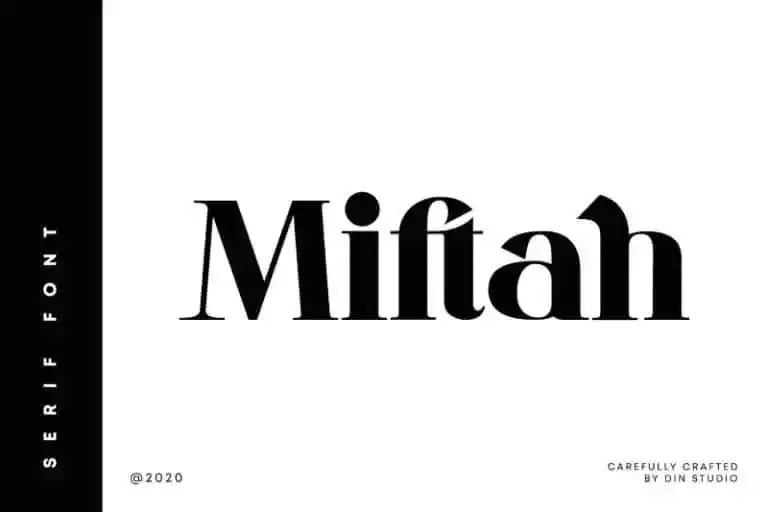
Miftah Serif Font – Download Grátis
A Miftah Serif Font é uma escolha perfeita para projetos profissionais que buscam a elegância clássica combinada com simplicidade moderna. Desenvolvida pelo Din Studio e oferecida pela 99designs, esta fonte serif representa um equilíbrio entre refinamento e minimalismo. Suas curvas elaboradas e formas únicas garantem uma aparência elegante para aplicações em cabeçalhos, logos ou até mesmo convites de casamento. Com seu design cuidadosamente criado, a Miftah Serif Font é ideal para qualquer projeto de marca que deseja transmitir um tom sofisticado e inovador ao público. Seu visual arredondado e detalhado torna-a uma excelente escolha para elementos visuais que exigem uma certa formalidade. A Miftah, assim como todas as fontes serif, pode contribuir significativamente para a identidade visual de seu projeto, fornecendo um toque diferenciador em design gráfico, logomarca ou qualquer elemento do website ou impressão que seja responsivo ao público-alvo. Não deixe de experimentar o poder desta fonte em sua próxima criação!